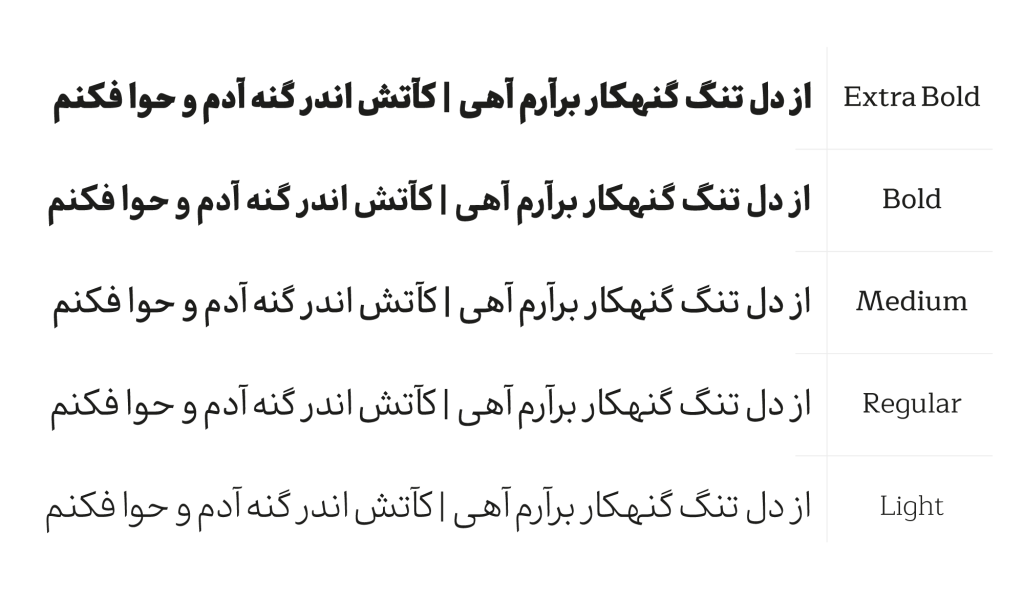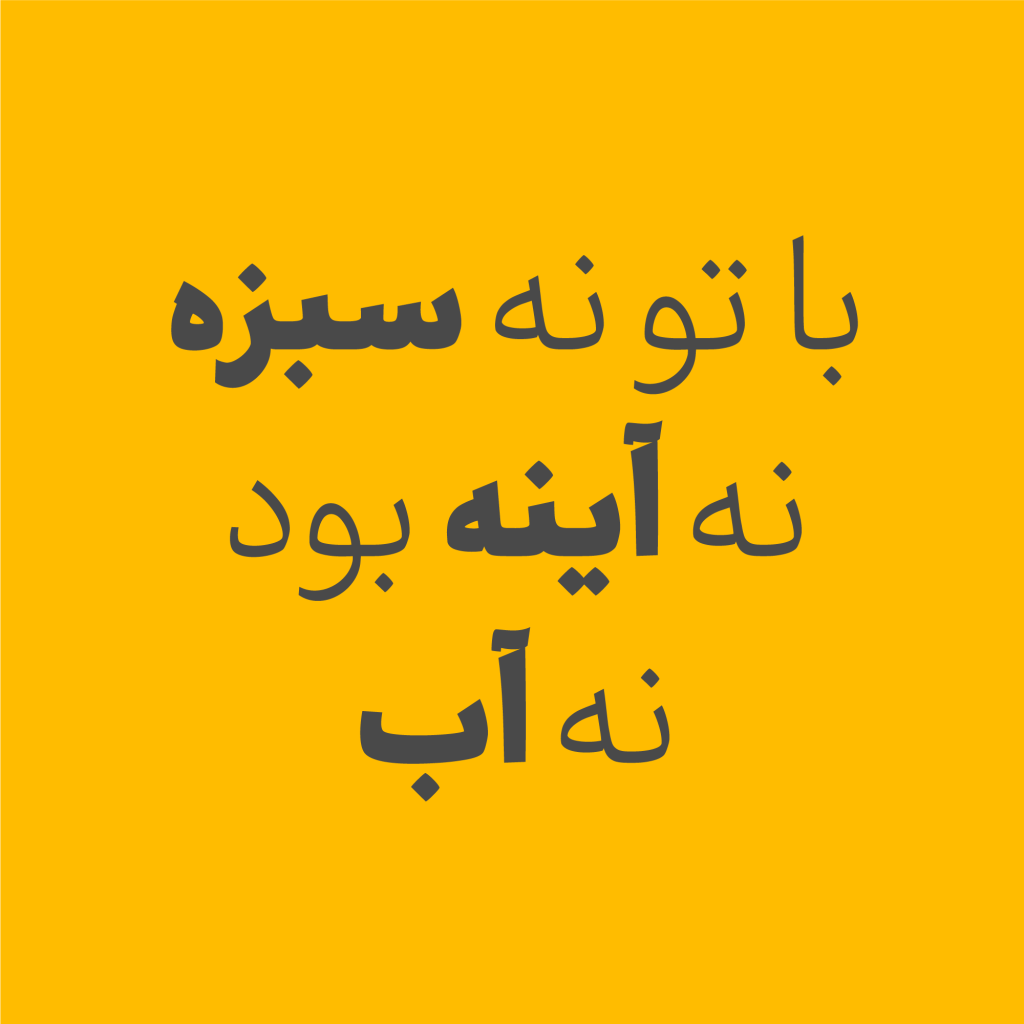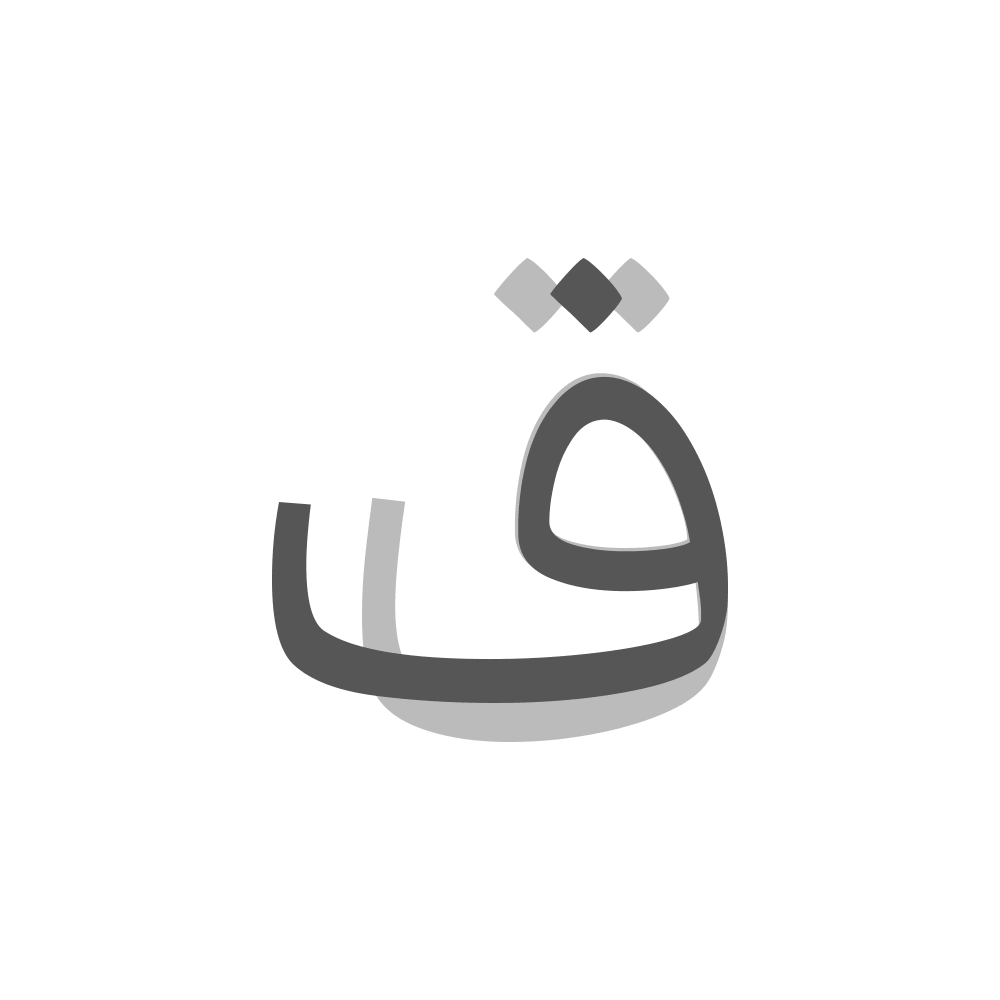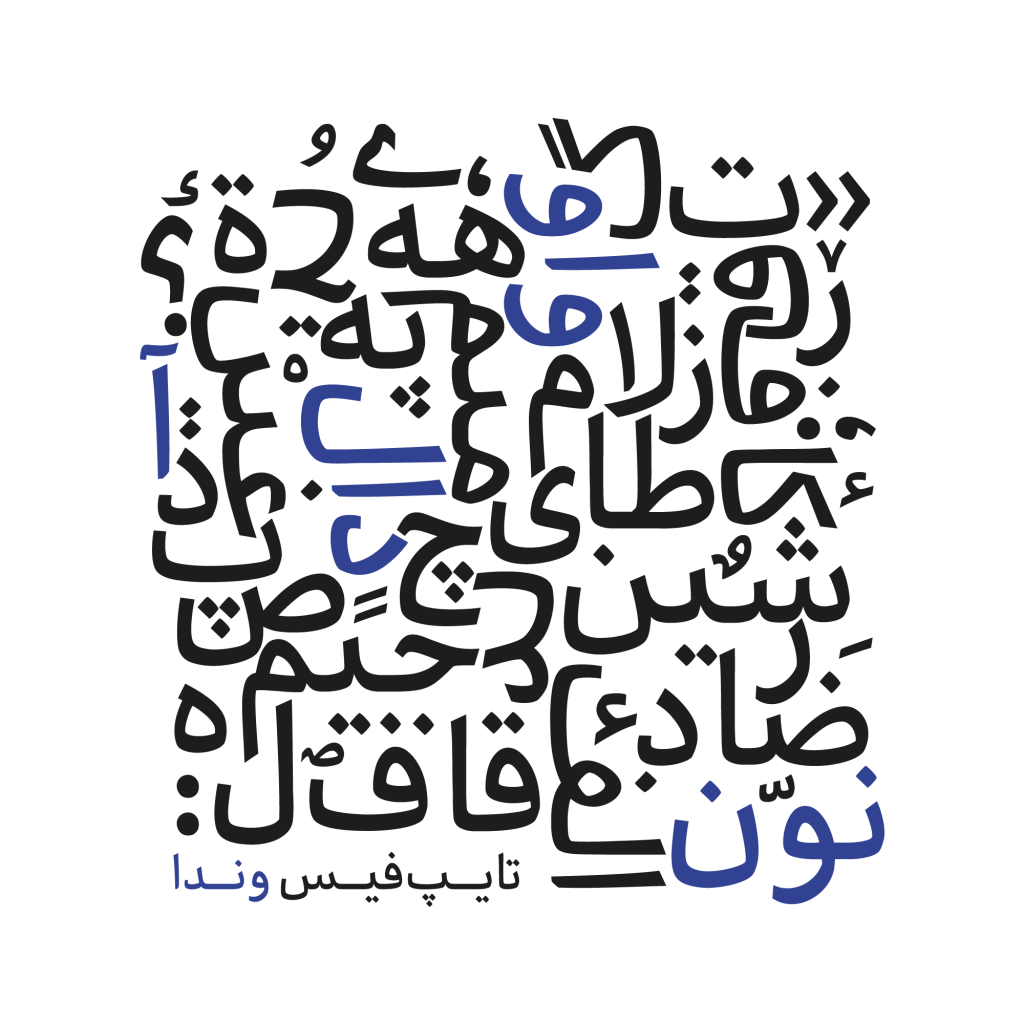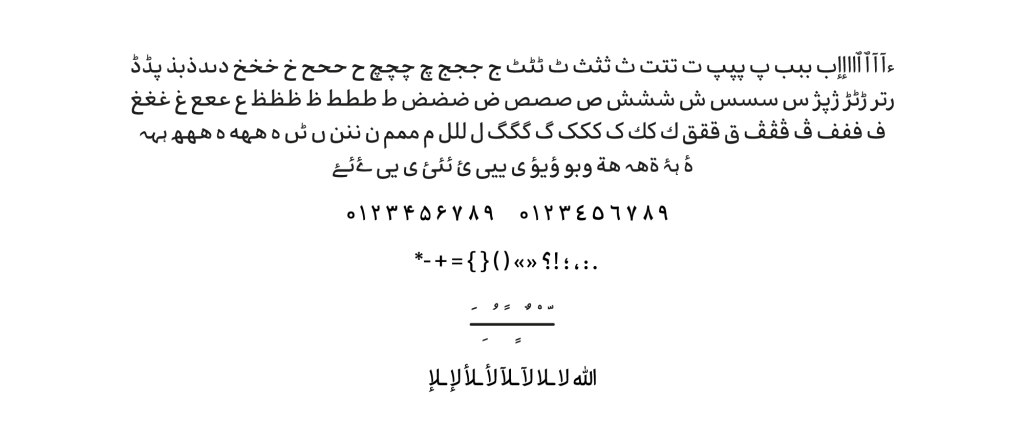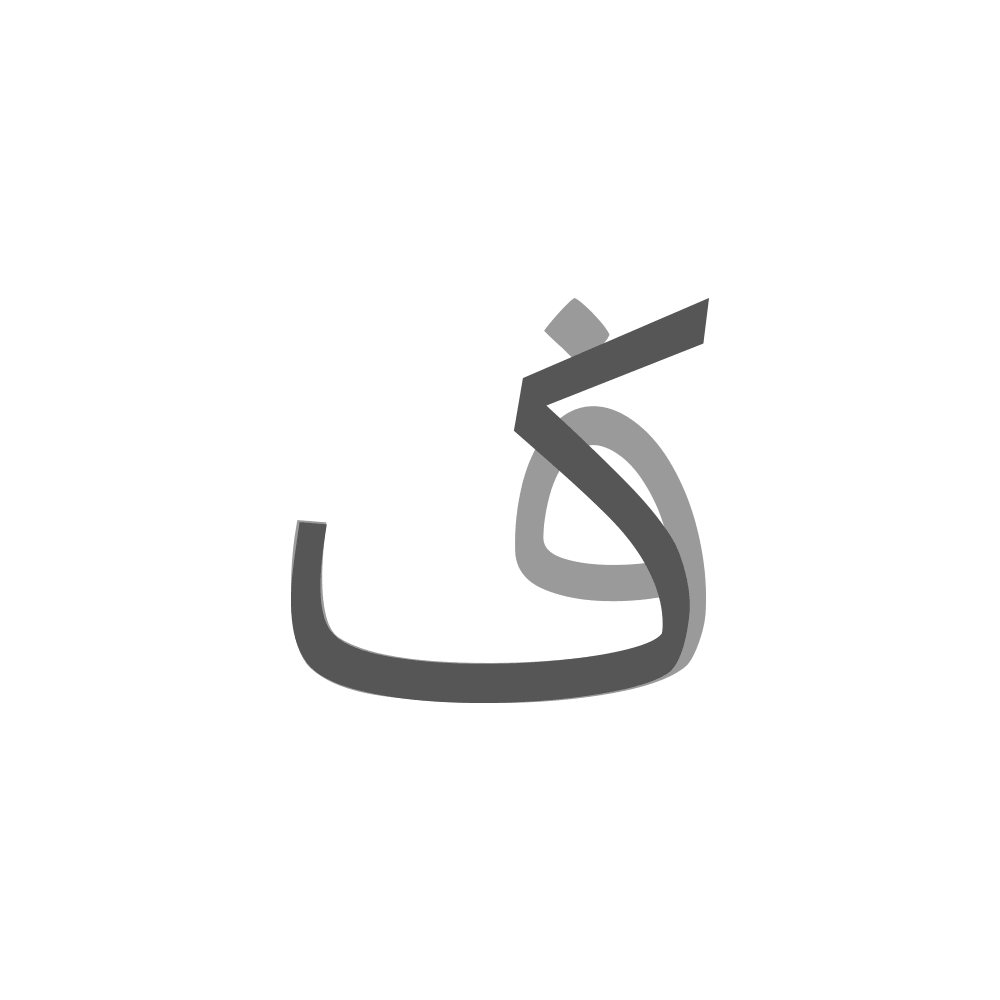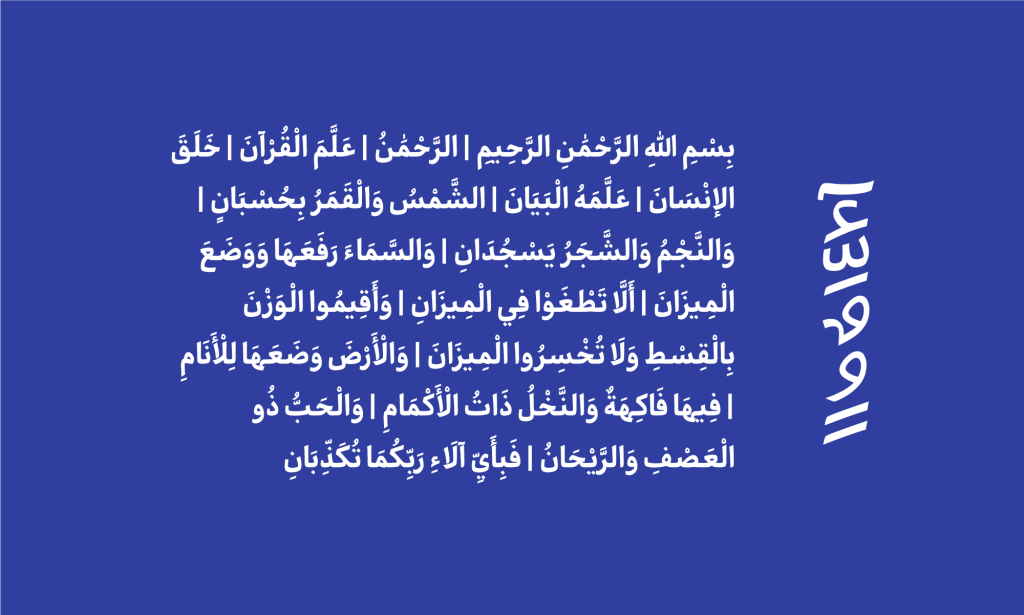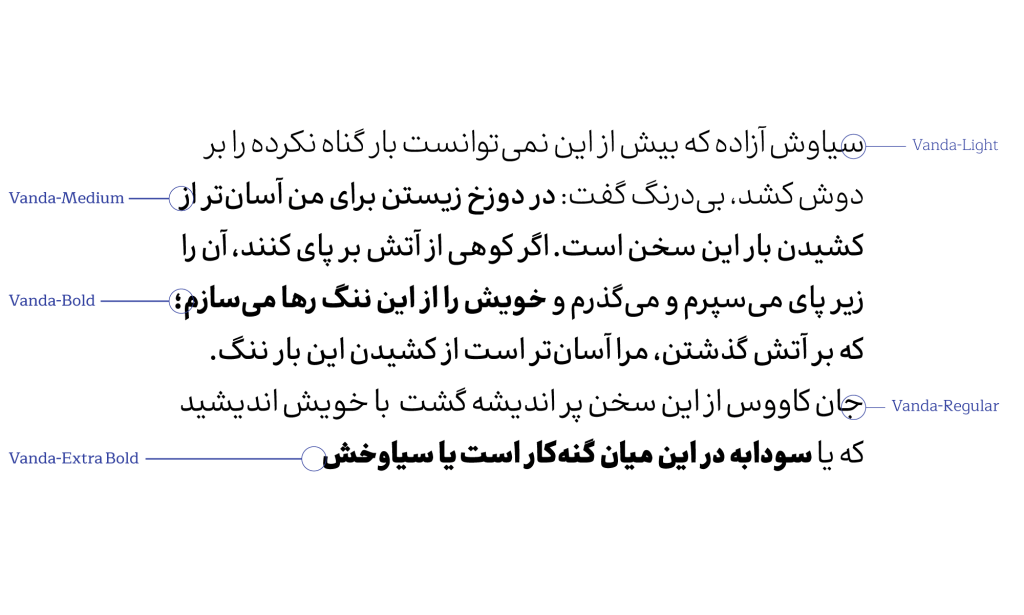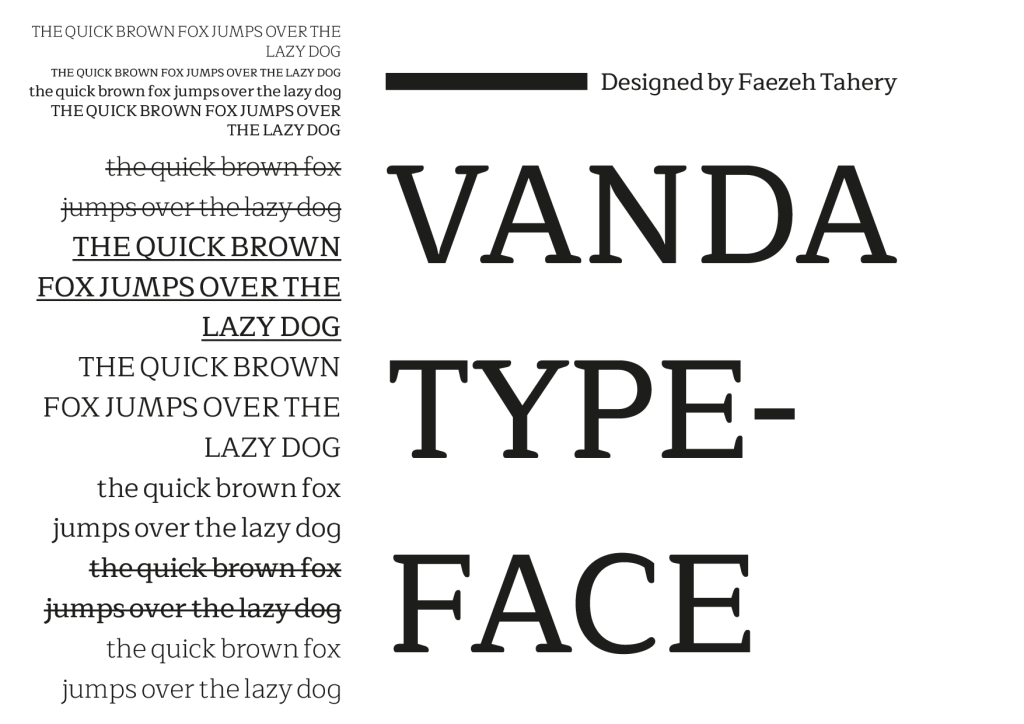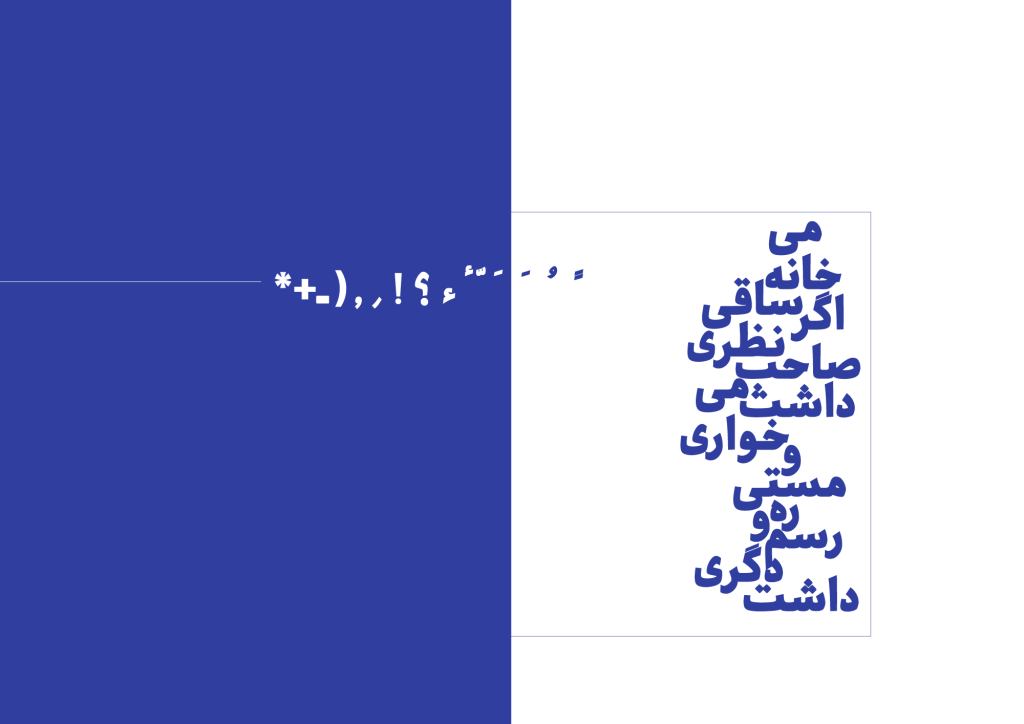
فونت وندا
تغییر ضخامت با کنتراست کم در خط بدنه از ویژگی های اصلی این تایپ فیس است.فونت وندا در گروه تایپ فیسهای کاملاً هندسی یا کاملاً خوشنویسانه قرار نمیگیرد؛ به همین دلیل فرم و لحنی مدرن دارد. بدنه و ساختار اصلی آن الهام گرفته از از فونت میترا می باشد.
با دقت می توان دریافت فضاهای منفی محصور در مقایسه با فضاهای مثبت و منفی غیر محصور موکدتر و هویداتر هستند. این نوع طراحی افزایش قدرت خوانش (Readability) و میزان تفکیک و تشخص بصری کاراکترها (Legibility) در سایزهای کوچکتر صورت گرفته است.
وندا شخصیتی جوان، ساده، بیآلایش و پویا و مدرن است در عین حال شخصیت و اصالت خود را دو چندان دارد.
فارسی ، عربی ، کوردی ، انگلیسی
5 وزن